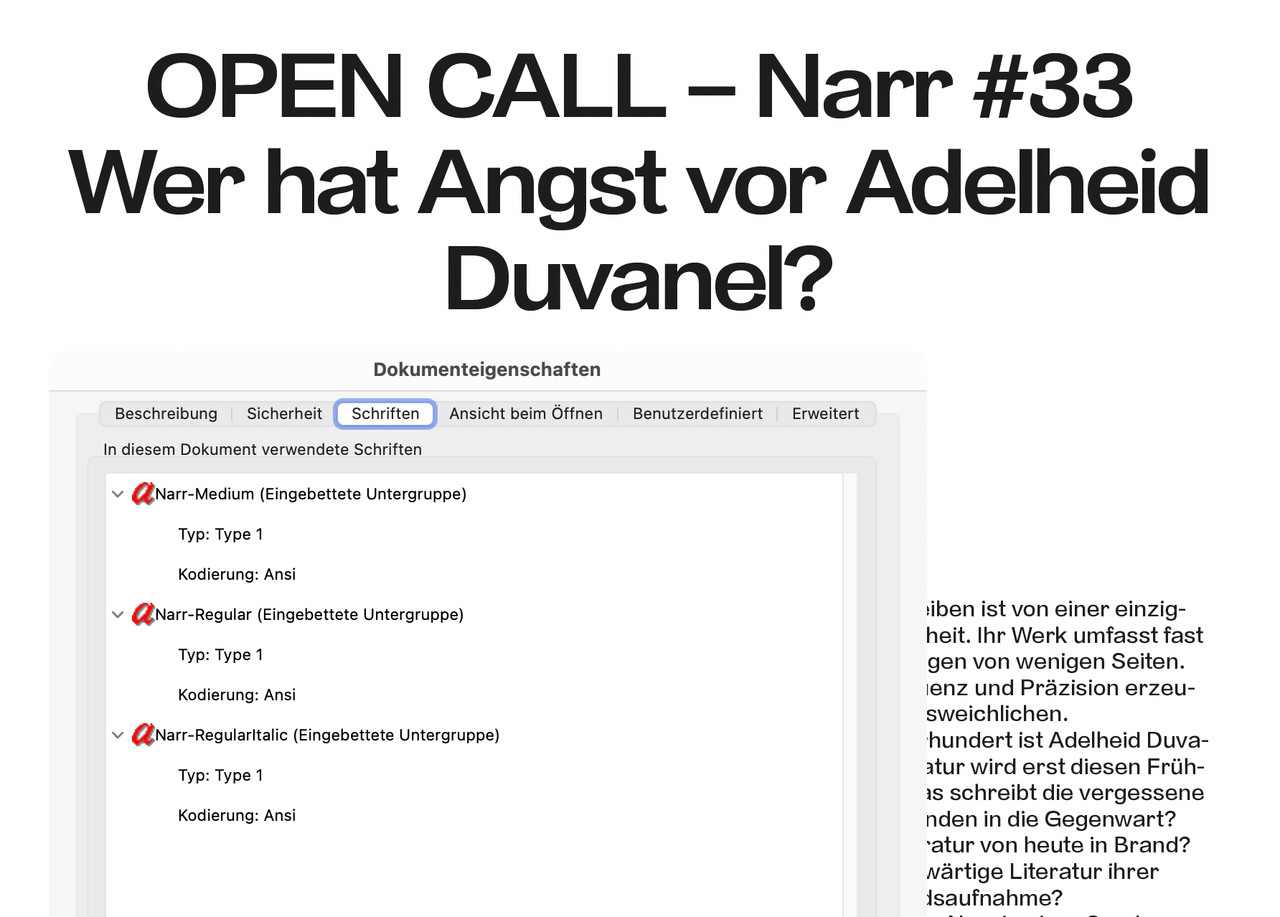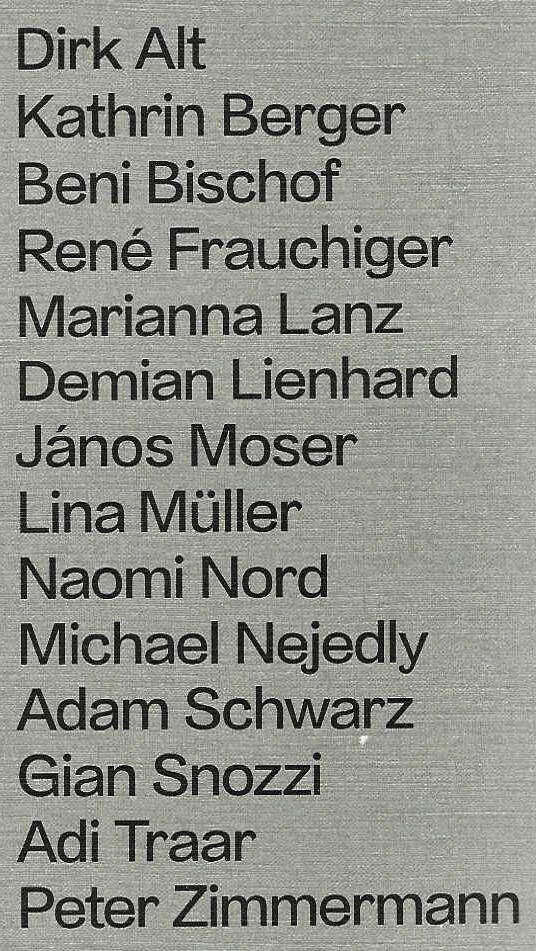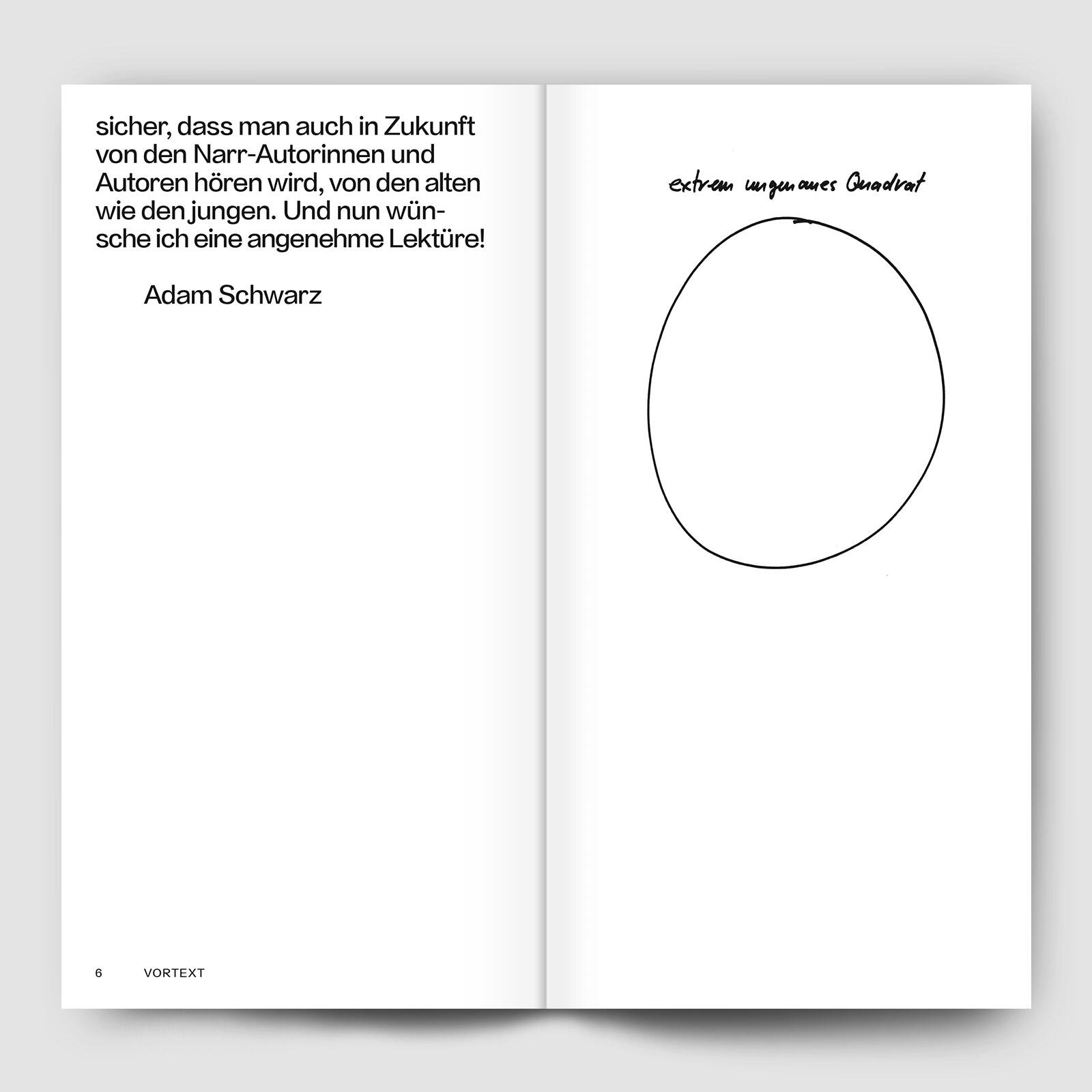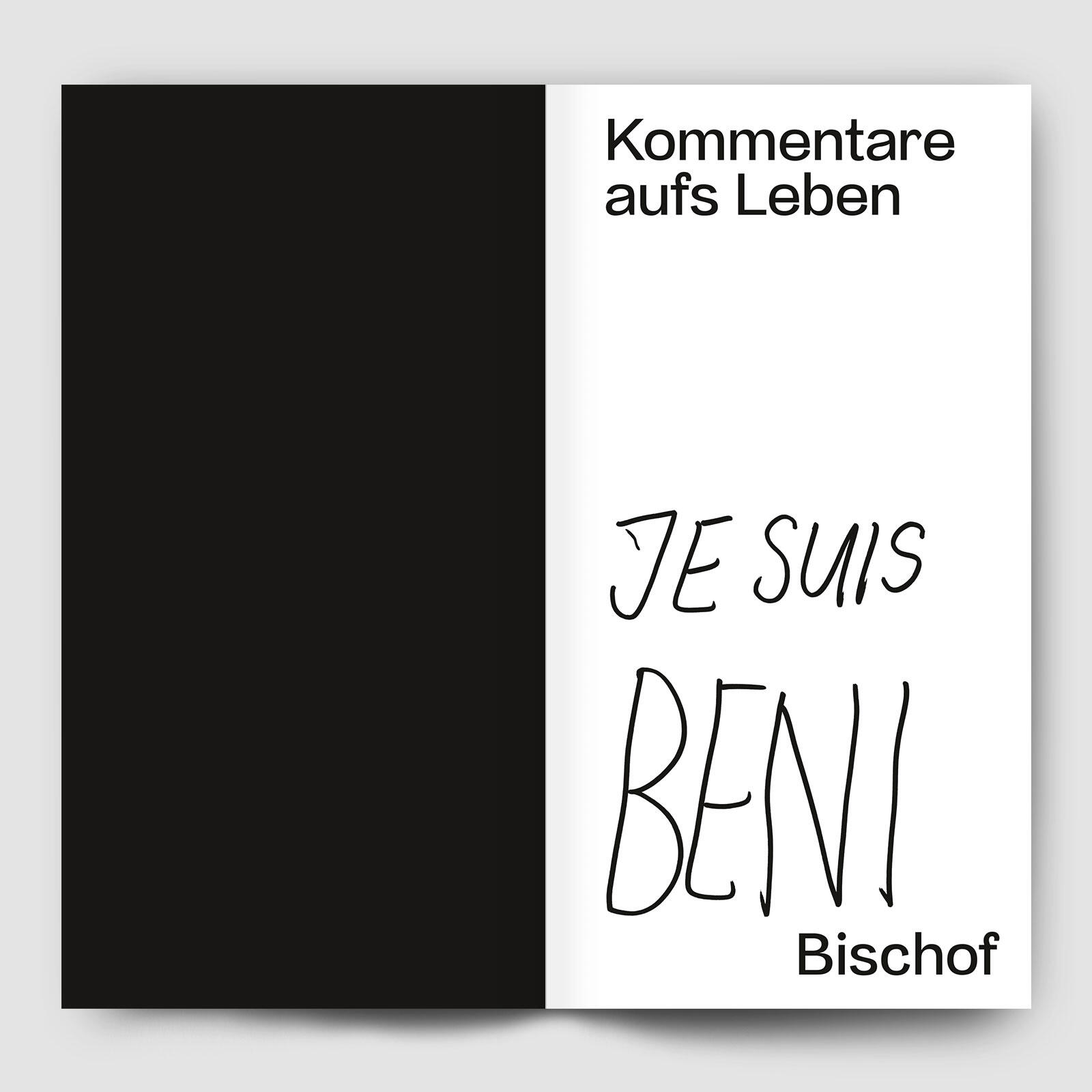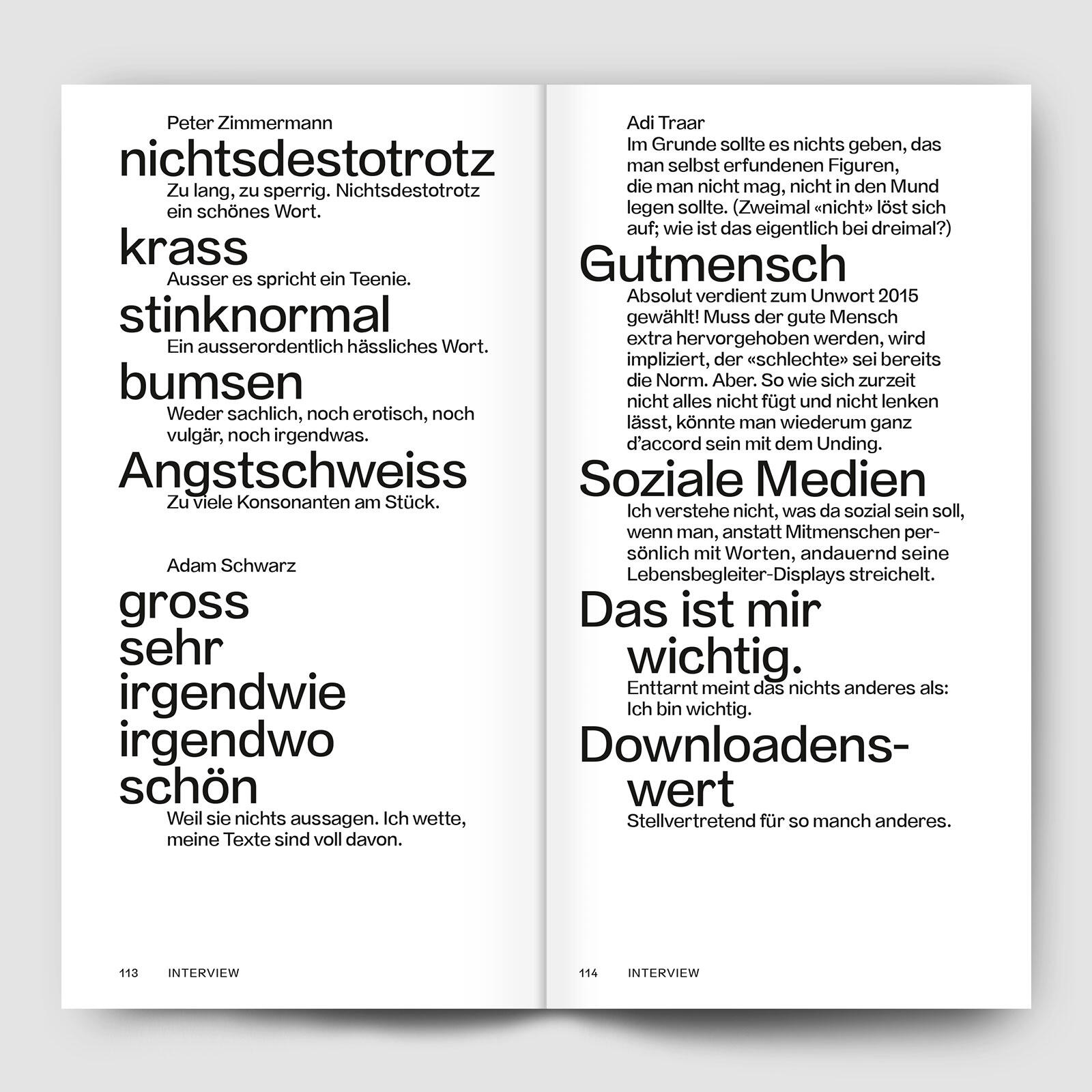
könnt ihr mir weiterhelfen? Das »f« ist besonders, der runde Punkt auf dem »i« – aber ich komme nicht weiter. Ist aus Das Narr #19, ein Literaturmagazin aus Olten (die Schrift innen, nicht die auf dem Cover).
Das ist beides die »Narr«, also eine Hausschrift. Ob exklusiv entworfen, weiß ich aber nicht.